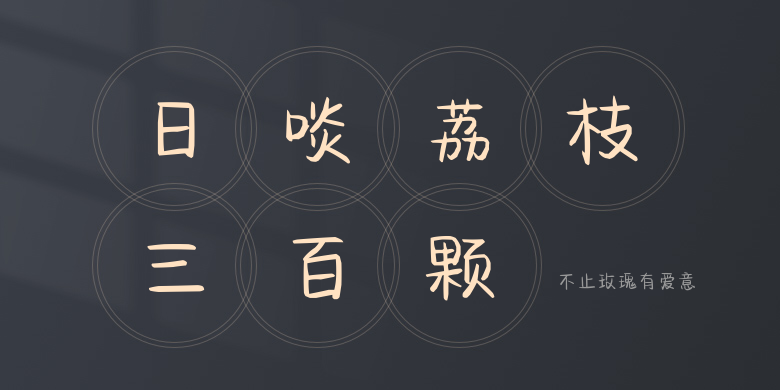
不止玫瑰有爱意
不止玫瑰有爱意,这款字体结构工整、笔画清晰,兼顾美观与易读性,适用于标题、正文、海报、包装、LOGO 等多种场景。字形优雅稳定,风格百搭耐看,适配日常排版与创意设计,让文字呈现更舒适、更具质感。不止玫瑰有爱意一笔一画,皆是细节,以均衡的比例、流畅的线条打造舒适视觉体验,字形端正大气,风格简约现代。无论是商业设计、品牌宣传还是日常排版,都能轻松驾驭,让文字更有格调与力量。不止玫瑰有爱意字体下载。